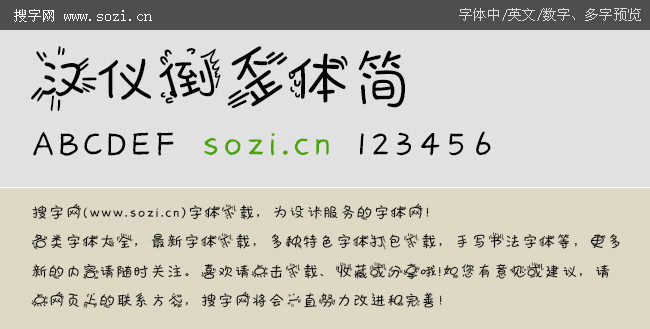
漢儀倒歪體簡
搜字網(wǎng)給大家提供一款漢儀倒歪體簡中文字體下載,漢儀倒歪體簡字體是一款非常有特色的卡通字體文件。字體倒歪著,字體筆畫設(shè)計添加了符號,顯得非常可愛。適用于兒童畫冊設(shè)計、卡通海報設(shè)計、包裝設(shè)計等場合使用。(本字體為個人非商用版,如需要商用請聯(lián)系漢儀公司購買版權(quán))